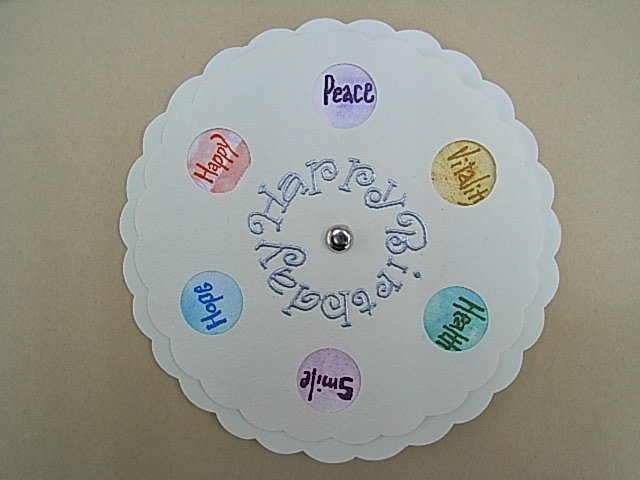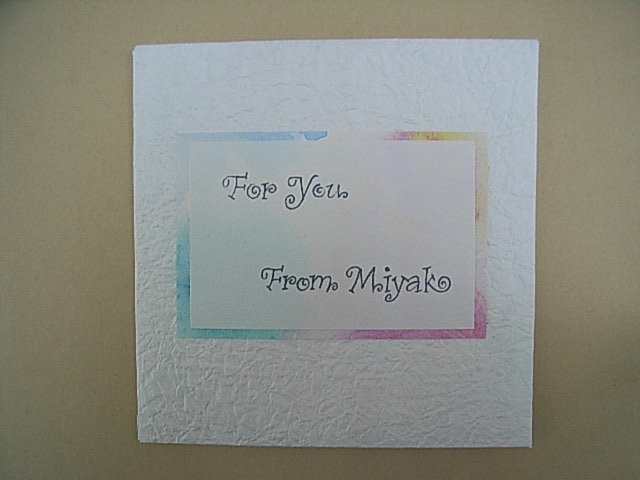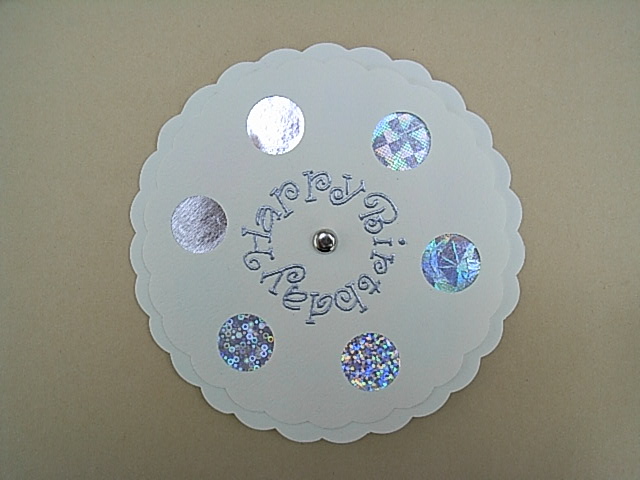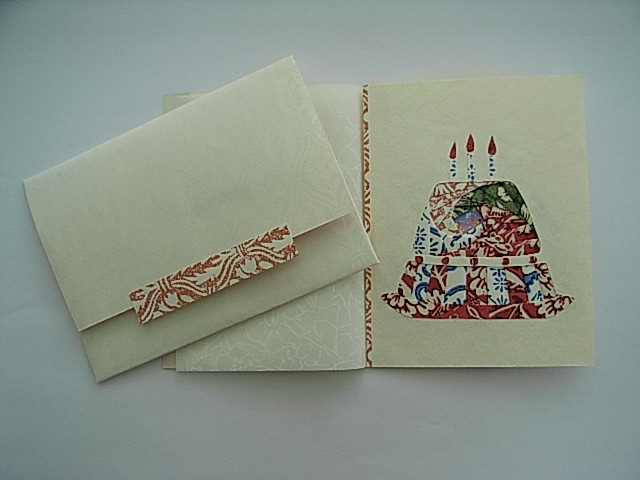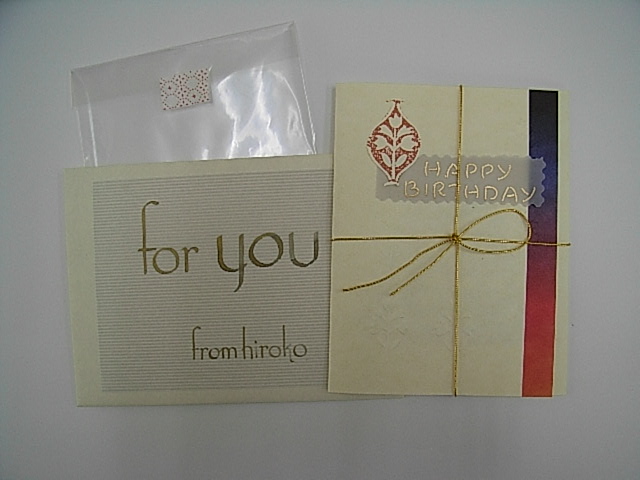
6月の誕生日カード
2回目になるモジトルカードエクスチェンジの6月のお誕生日カードのご紹介です。
さて、カードですが、お二人にお届けしたカードは、前回に引き続き参加された、HNさんとMKさんのカードです。
HKさんのカードは、和紙を使い、和モダンのテイストがいかされています。カード、封筒とも素材、色、模様を合わせが細やかで美しいです。
封筒とカード表、それを入れるビニールです。
カードは、グラデーションがきれいな帯、裏の模様の一遍とHAPPY BIRTHDAYをコラージュして、ゴム状の紐で結ばれています。ビニールのテープは、トレンドのmtテープです。
封筒とカードの裏です。
カードを開くと彩り豊かな折重ねられた和紙が、ケーキをかたどっています。
なんという技術なのでしょう?知識なく説明できずもうしわけありませんが、手が込んでいるなあと感心してしまいました。
MKさんのカードは、いうまでもなく、いつもアイデアいっぱいで楽しく、技術高い完成されたものですね。
これは、封筒です。和紙、WASHのグラデーションがきれいです。
カード本体は、中央がピンでとめてあり、内側の円が動くようになっています。小さな円からのぞいているのは、シルバーのいろいろな模様が華やかです。HAPPY BIRTHDAYの文字は、エンボス加工された、ポップな文字で楽しい雰囲気いっぱいです。
そして、内側の円を回転させると、もっと楽しくなるカラフルな色とPeace, Happy, Vitality, Hope, Health, Smileの言葉がが現れます。 お誕生日に際して、嬉しい言葉の数々ですね。
カード制作は、小さいけれど、アイデアをまとめるのがたいへんな作業かもしれません。でも、きっと皆さん手が動き出すと止まらないかんじでしょうか?これからまた、どんなカードを見ることができるかとても楽しみです。